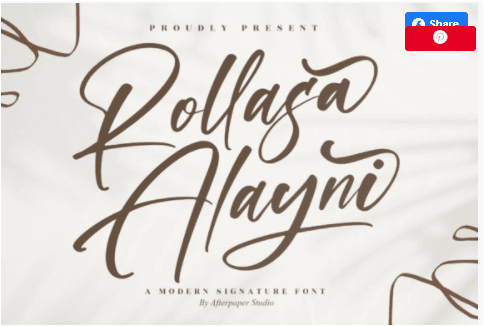
Rollasa Alayni Font
Rollasa Alayni — изящный, элегантный и плавный рукописный шрифт. У него красивые и хорошо сбалансированные персонажи, и в результате он подходит для широкого круга дизайнов. Rollasa Alayni имеет кодировку PUA, что означает, что вы можете легко получить доступ ко всем глифам и росчеркам!